손글씨 무료 폰트는 감성과 개성을 더해주는 디자인 요소입니다.
요즘과 같이 다양한 매체를 통해서 자신이나 기업을 PR 해야 하는 시기일수록 작은 디테일의 차이로
가치가 평가될 수 있는데요. 그 때 시각적으로 중요한 요소가 폰트 스타일입니다.
고유한 무드를 적절하게 드러내면서 알찬 콘텐츠를 기획한다면 손글씨 폰트는 매우 중요한 요소가
될 수 있습니다. 다만, 비용을 절감하면서 콘텐츠 제작에 힘쓰고 싶은 분들에게 손글씨 무료 폰트 다운로드는 매우 유용한 자산이 될 수 있습니다.
손글씨 무료 폰트 왜 필요할까?
디지털 콘텐츠가 넘치는 시대입니다. 그 속에서 ‘개성’은 곧 ‘차별화’입니다.
손글씨 무료 폰트는 자연스럽고 따뜻한 느낌을 줄 수 있어 콘텐츠에 감성을 더해줍니다.
손글씨 무료 폰트의 인기 이유
손글씨체는 블로그, 유튜브, 전단지, 카드뉴스, 인스타그램 등 다양한 플랫폼에서 활용됩니다.
특히 감성을 자극하는 디자인에서 높은 반응을 보입니다.
감성적 터치 하나가 클릭률을 최대 37% 이상 높일 수 있다는 분석도 있습니다.
상업적 사용 가능한 손글씨 무료 폰트 추천
다음은 무료이면서 상업적으로도 사용할 수 있는 손글씨 폰트입니다.
| 배민체 | 배달의 민족 | https://www.woowahan.com/fonts | 귀엽고 자연스러운 손글씨 느낌 | 상업적 사용 가능, 출처 불필요 |
| 서울한강체 | 서울시 | https://www.seoul.go.kr/seoul/font.do | 한강의 물결, 서울의 역동성 담은 깔끔하고 친근한 느낌 고딕계열 폰트가독성 우수, 현대적 감성 표현 | 공공저작물, 자유 이용 가능 |
| 네이버 한글한글아름답게 | 네이버 | https://hangeul.naver.com/font | • 마루 부리, 나눔 손글씨 등 다양한 폰트 제공 • 네이버에서 제작한 고품질 한글 폰트 • 정기적으로 새로운 폰트 업데이트 |
| 구글 폰트 | 구글 | https://fonts.google.com/?subset=korean | • 나눔 손글씨, 포천 오성과 한음체 등 제공 • 웹폰트로 쉽게 적용 가능 • 다양한 두께와 스타일 제공 |
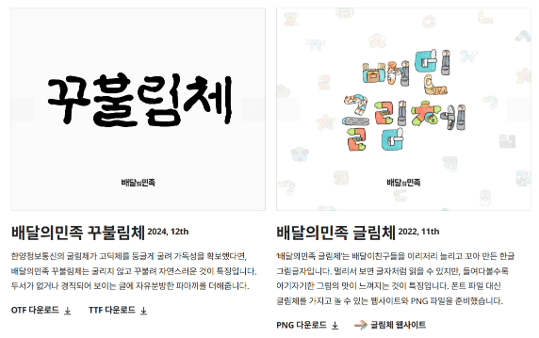
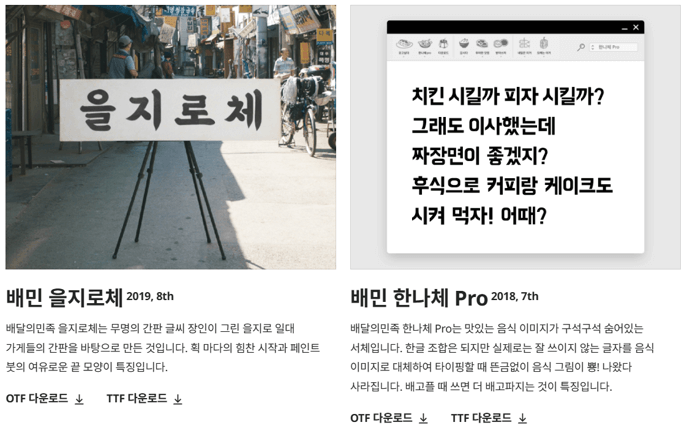
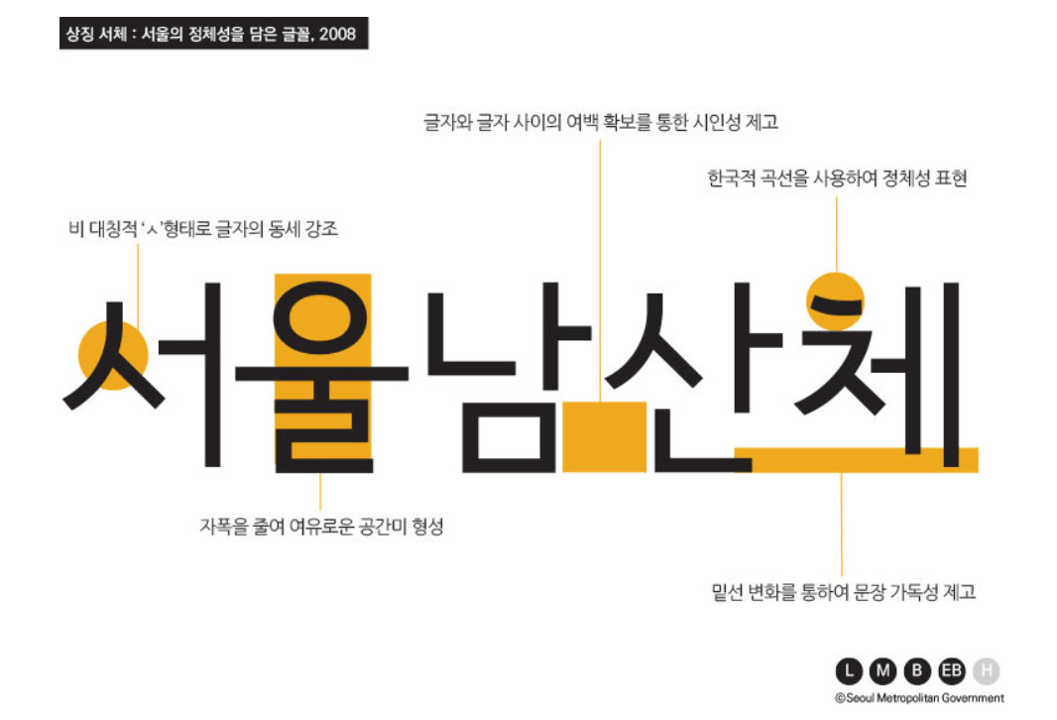
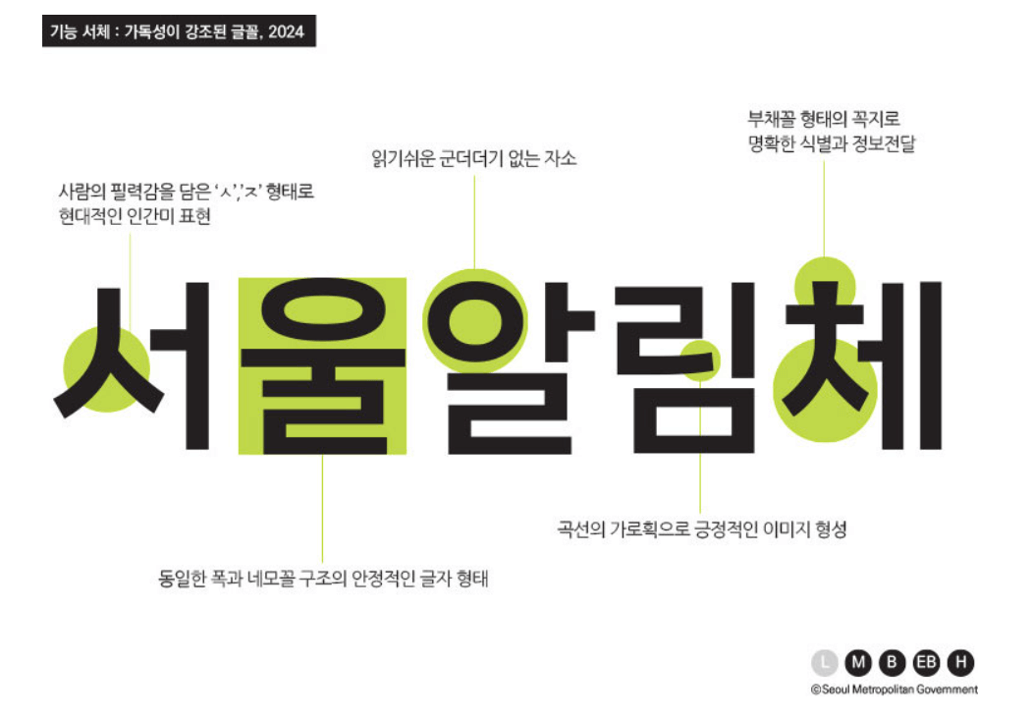
콘텐츠는 디테일에서 신뢰를 얻습니다.
손글씨 무료 폰트는 작은 감성으로 큰 결과를 만들 수 있습니다.
이제 저작권 걱정 없이 사용할 수 있는 안전한 폰트를 잘 선택하여 더 멋진 콘텐츠를 만들어 보세요.
단순한 텍스트 하나가 곧 당신의 ‘브랜딩’이 될 수 있습니다.